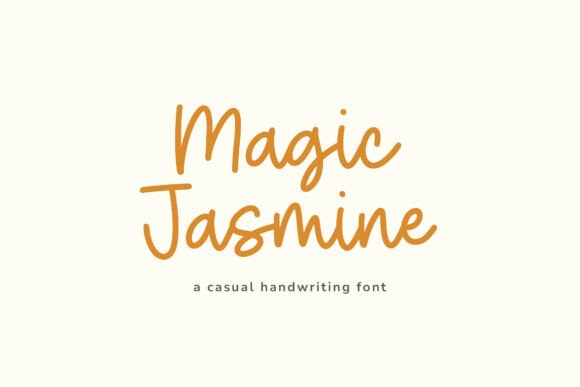
Magic Jasmine
إذا كنت تبحث عن أصول عالية الجودة مثل Magic Jasmine، فإن هذه الحزمة المميزة هي خيار رائع لمشاريعك الإبداعية.
تم تصميمه بدقة، ويوفر Magic Jasmine متجهات نظيفة وطباعة سلسة وترخيصًا تجاريًا لراحة بالك.
سواء كنت تقوم بإنشاء منتجات الطباعة عند الطلب أو دعوات الزفاف أو رسومات وسائل التواصل الاجتماعي، فإن Magic Jasmine هو الخيار المثالي.